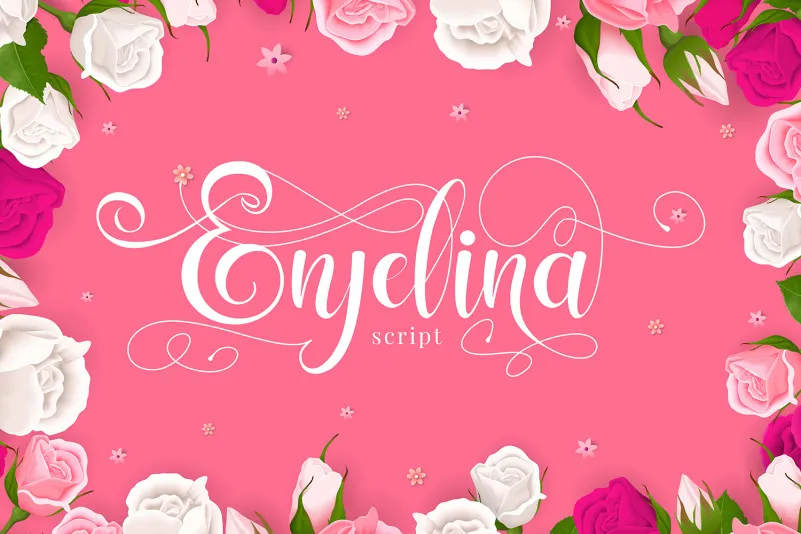
Enjelina Sweet Script Font – Download Grátis
A fonte ‘Enjelina Sweet Script Font’ oferece uma abordagem delicada e encantadora para projetos digitais, especialmente adequada aos requisitos que exigem um toque de elegância e romantismo. Este belo script foi criado com a intenção de enriquecer designs em áreas como logos, marcas de marca, embalagens de produtos, sacolas de shopping, cartões de convite, capas de livros e mesmo até pequenos detalhes como marcos fotográficos. Seus traços suaves e delicados não apenas ajudarão a tornar qualquer projeto mais bonito e profissional, mas também lhe dará o poder de expressar sentimentos sutis e nuances em uma linguagem visual única. Com ‘Enjelina Sweet Script Font’, designers podem explorar as possibilidades criativas sem ter que se preocupar com as limitações de um estilo de fonte mais tradicional. É perfeito para qualquer projeto que exija delicadeza, charme e personalização única.